Majuskelziffern
Typografischer Terminus für die Indo-Arabische Ziffern 1, 2, 3, 4, 5, 6, 7, 8, 9 und 0 ohne variierende Oberlängen und Unterlängen im Zweiliniensystem, die im typometrischen Hauptschriftliniensystem von der Grundlinie bis zur H-Linie (Majuskelhöhe) reichen.
Etymologisch aus »Majuskel« vom mlat. »maiuscula« (litera) zu lat. »maiusculus« für »etwas größer« zu lat. »maior, maius« für »größer« und »Ziffer« für arab. »as-sifr«, mlat. »cifra« oder »cephirum«, sphd. »zif(f)er«. Auch als Versalziffern (siehe Versalien) bezeichnet. 1)
Majuskelziffern als physischen Drucktypen aus Metall (z.B. aus einer Blei-Zinn-Antimon-Kupfer-Legierung), Holz (z.B. aus Birnenholz) oder Kunststoff (z.B. aus Kunstharz) wurden sowohl in der Schriftgattung der Gebrochenen Schriften als auch bei Antiqua-Schriften Anfang des 19. Jahrhunderts im Zuge der Prosperität von Akzidenzdrucksachen aus den Mediävalziffern entwickelt. Traditionell wurden in der Antiqua-Typografie (uspr. Englische Typografie) bei Buch- und Zeitungsschriften sowie bei Kapitälchen primär Minuskelziffern, bei Akzidenzschriften und im Titelsatz mehrheitlich Majuskelziffern verwendet. Mutmaßlich wurden in der Deutschen Fraktur-Typografie mit Beginn des 19. Jahrhunderts – auch in der Buchtypografie – überwiegend Majuskelziffern genutzt.
Majuskelziffern gibt es in allen erdenklichen Schriftbreiten, Strichstärken und Schriftlagen, mit und ohne Serifen, als Proportionalziffern (siehe Proportionalschrift) und Tabellenziffern (siehe auch dicktengleich) sowie in Form von Bruchziffern. 2) 3) 4)
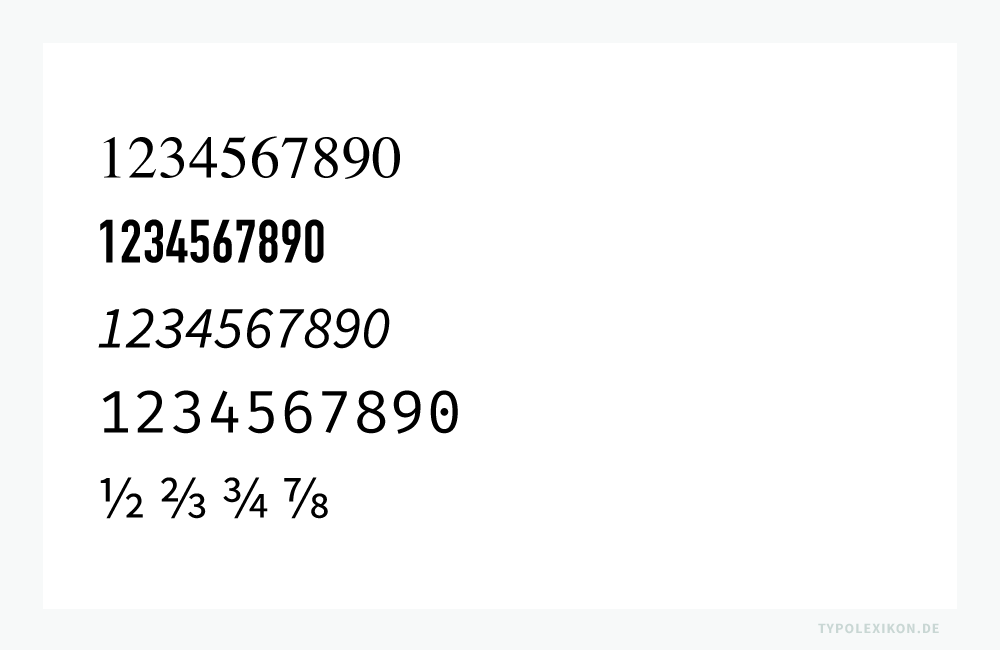
Ob im Zeichenvorrat eines Schriftschnitts Majuskelziffern oder Mediävalziffern – oder gar beide – enthalten sind, dafür gibt es heute keine festen Regularien. Bei OpenType Fonts können unterschiedliche Ziffernvarianten als Glyphen hinterlegt sein, beispielsweise auch Kapitälchenziffern, die auf den ersten Blick den Majuskelziffern sehr ähnlich sehen.
Thesen zu Majuselziffern (Versalziffern)
- Majuskelziffern eignen sich optimal für den Tabellensatz und Formelsatz, idealerweise in Form von Tabellenziffern, da sie einheitlich auf der Grundlinie stehen und auch bei größeren Satzspaltenabständen, z.B. in einer Bilanz oder GuV-Rechnung, eine ruhige, nicht flatterhafte Linie für das Lesen (siehe Fixationen) einer Zahlenreihe bieten.
- Bei Verlags-, Zeitungs- und Buchschriften bzw. im Mengensatz (Werksatz) sollten im geschlossenen Schriftsatz grundsätzlich keine Majuskelziffern, sondern ausschließlich Mediävalziffern verwendet werden, da diese sich aufgrund ihrer wechselnden Ober- und Unterlängen ästhetischer in einen Fließtext einfügen und somit den Leserhythmus nicht unnötig stören.
- Bei buchähnlichen Publikationen, z.B. Geschäftsberichten oder Produktkatalogen, sollten sowohl Majuskelziffern als auch Minuskelziffern verwendet werden, wobei die Mediävalziffern im Fließtext, die Minuskelziffern (bestenfalls als Tabellenziffern) in Zahlentabellen bzw. Zahlenreihen verwendet werden.
- Im Antiqua-Schriftsatz mit Kapitälchen werden aus ästhetischen Gründen traditionsgemäß keine Majuskelziffern, sondern Mediävalziffern verwendet.
- Bei primären Systemschriften sind Majuskelziffern die Regel. Bei sekundären Systemschriften gilt das gleiche, wobei es hier einige wenige Ausnahmen gibt, beispielsweise die »Georgia« von Matthew Carter, die Mediävalziffern enthält.
- Wer in HTML-Fließtexten Majuskelziffern vermeiden möchte, muss Webfonts mit Mediävalziffern (bei normaler Tastaturbelegung) einbinden.
| ↑1 | Anmerkung: Die häufig verwendete Bezeichnung »Normalziffer« für eine Majuskel- bzw. Versalziffer ist de facto inkorrekt. |